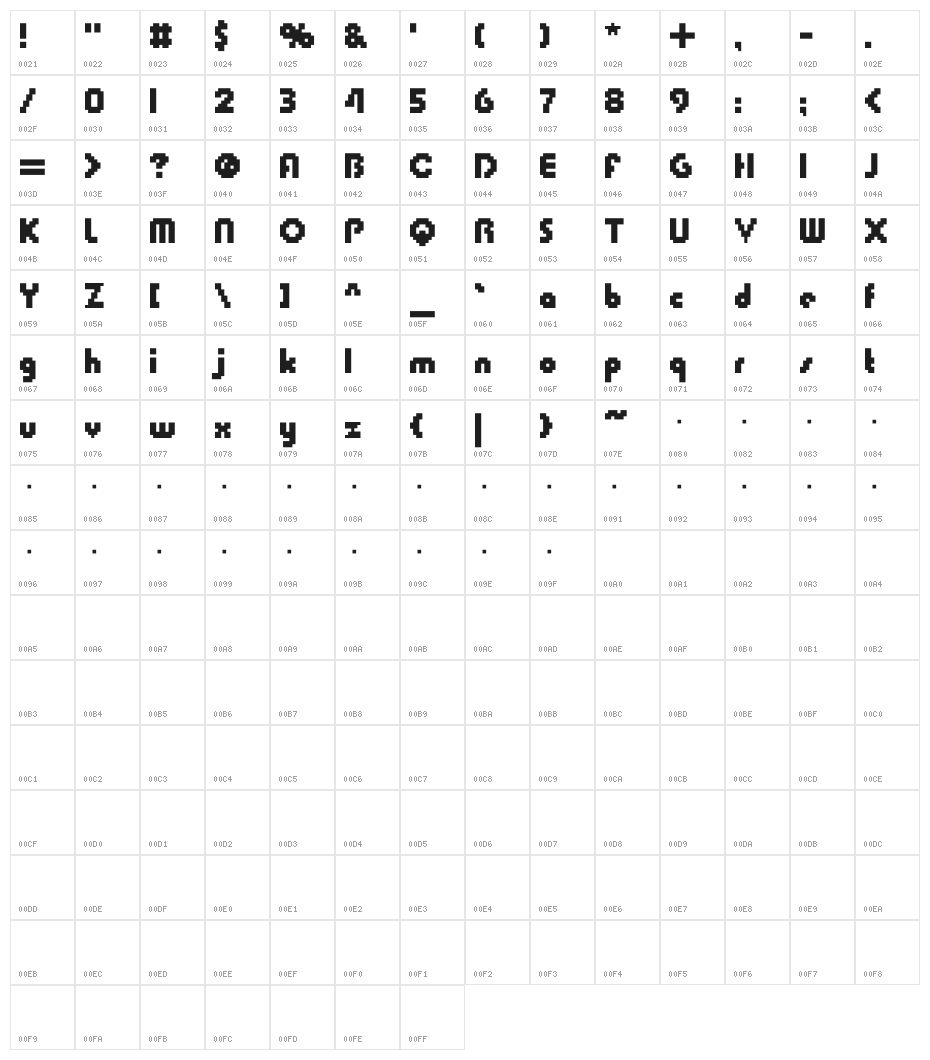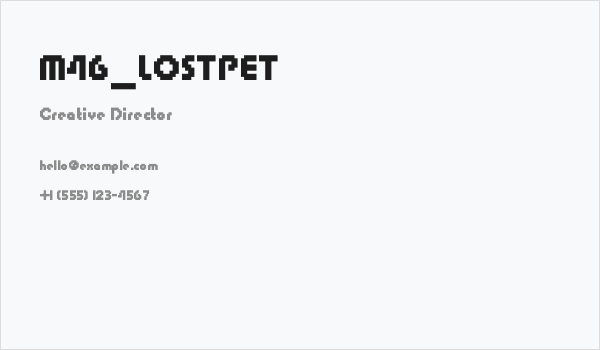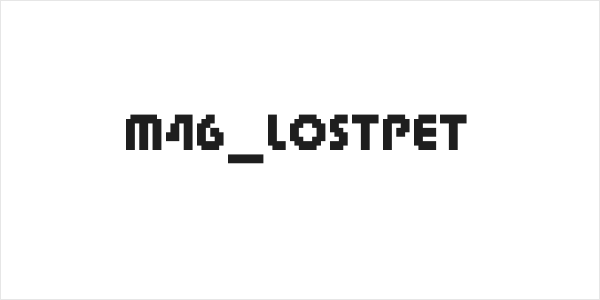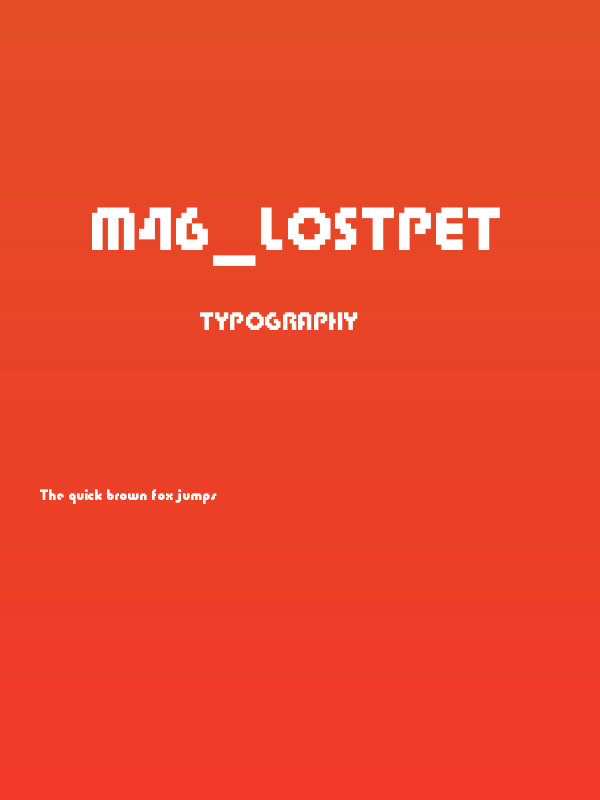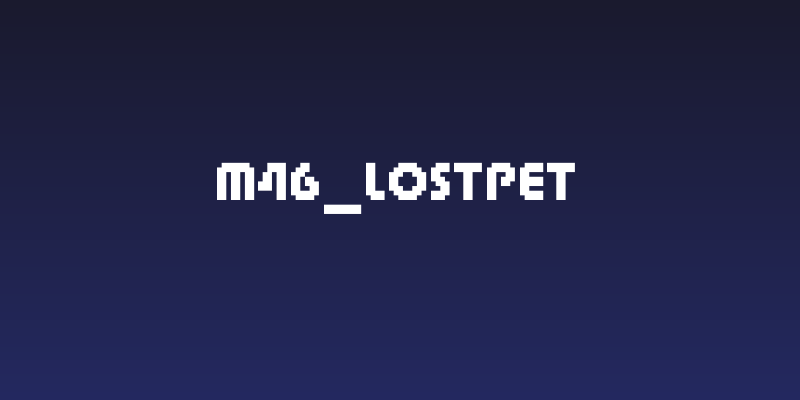
M46_LOSTPET Font
| Categorie | Pixel |
| Stile generale | Retro, Digital |
| Progetti proposti | Ideal for video game design, retro-themed posters, digital art projects, and any creative work that seeks to capture a nostalgic digital vibe. |